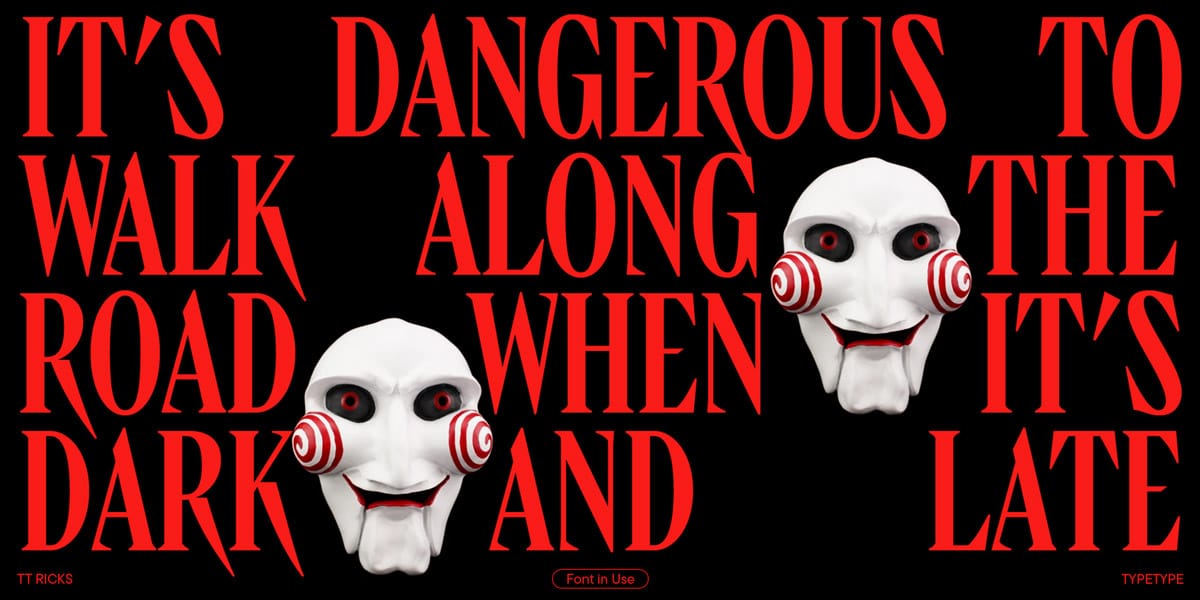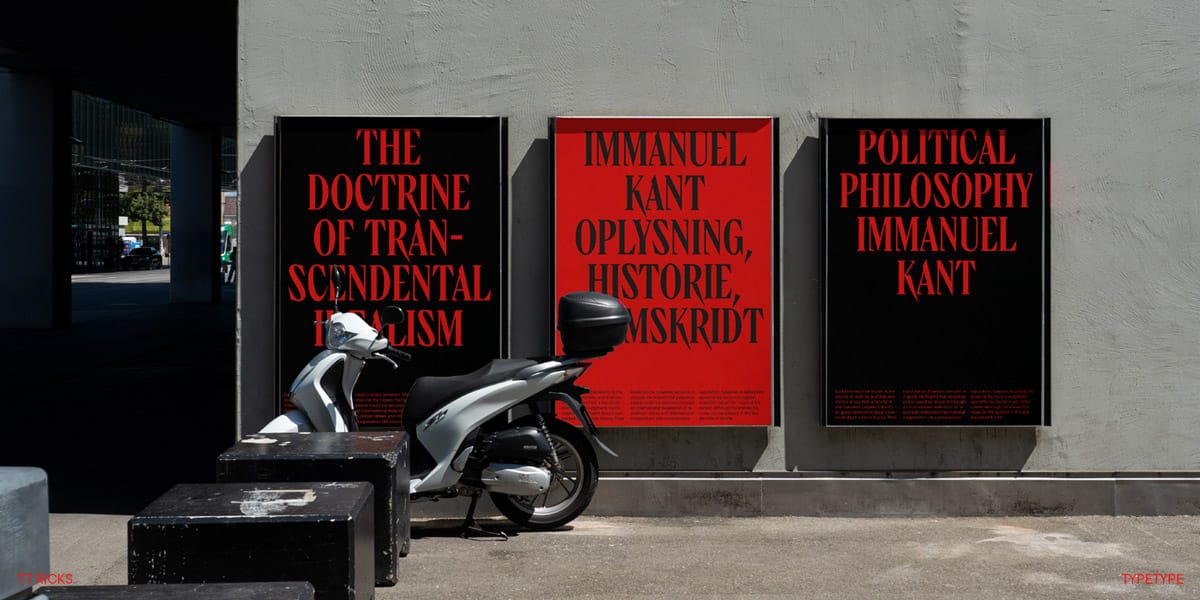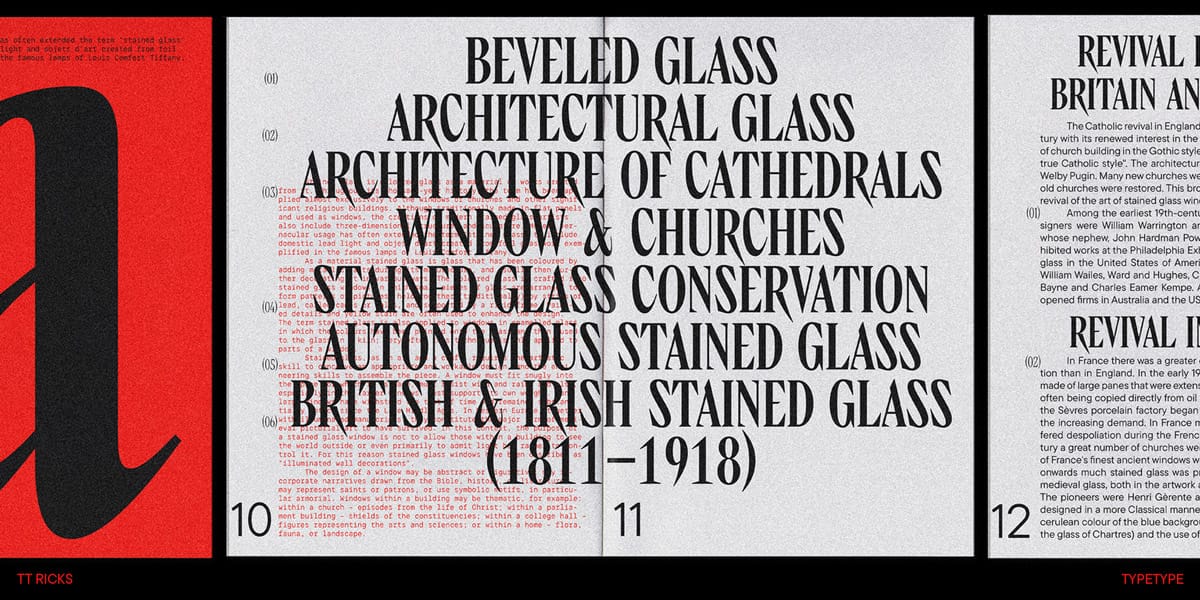
TT Ricks là một bộ font serif cá tính mạnh, sắc nhọn và đầy “góc cạnh”. Font chữ có tỷ lệ hẹp, độ tương phản cao và các chân serif giống như gai nhọn, tạo nên ấn tượng táo bạo và hung hãn.
Giới thiệu về TT Ricks
TT Ricks trong phiên bản mới nay đã hỗ trợ bảng chữ cái Cyrillic. Phiên bản cập nhật mang đến bộ ký tự phong phú hơn, cải thiện kerning và hinting, đồng thời bổ sung các tính năng OpenType mới cùng những bộ stylistic sets.
TT Ricks là một font serif giàu biểu cảm với tính khí gai góc. Font chữ được lấy cảm hứng từ kiểu chữ De Vinne cổ điển, do Gustav F. Schroeder thiết kế năm 1892. Khi phát triển TT Ricks, tác giả giữ lại một số đặc điểm của nguyên mẫu lịch sử, nhưng đồng thời phá vỡ những khuôn mẫu cũ để tạo nên một cá tính hoàn toàn mới, mang đến diện mạo tươi mới và sống động hơn cho font chữ.
TT Ricks nổi bật nhờ độ tương phản cao, dáng chữ hẹp và các serif trông như gai nhọn. Font chữ sở hữu nhiều chi tiết độc đáo, chẳng hạn như trục oval chéo trong các ký tự bo tròn (c, e, s), các chữ thường Latin có thiết kế đặc trưng, hay phần nét đi xuống bất đối xứng trong các chữ Дд và Цц.
Trong phiên bản cập nhật, kerning và hinting được được tinh chỉnh lại kỹ lưỡng. Bảng chữ cái Cyrillic được bổ sung, cùng với việc mở rộng bảng Latin hiện có. Bộ ký hiệu tiền tệ cơ bản được mở rộng và thêm các ký hiệu tiền tệ dạng chữ thường, bao gồm cả phiên bản tabular cho cả chữ hoa và chữ thường. Bộ font chữ cũng được bổ sung phân số, chữ số cho tử số và mẫu số, cùng các chữ số khoanh tròn.
Ngoài ra, TT Ricks phiên bản 2.000 còn có các stylistic sets mới cho Cyrillic và một bộ biểu tượng gốc phong phú, giúp mở rộng phạm vi ứng dụng và làm nổi bật cá tính của phông chữ hơn nữa.
TT Ricks thể hiện tốt nhất ở cỡ chữ trung bình và lớn, nơi nó thu hút sự chú ý tối đa. Font chữ này đặc biệt phù hợp cho thiết kế bao bì, poster và đồ họa sách.
TT Ricks Font Family Preview